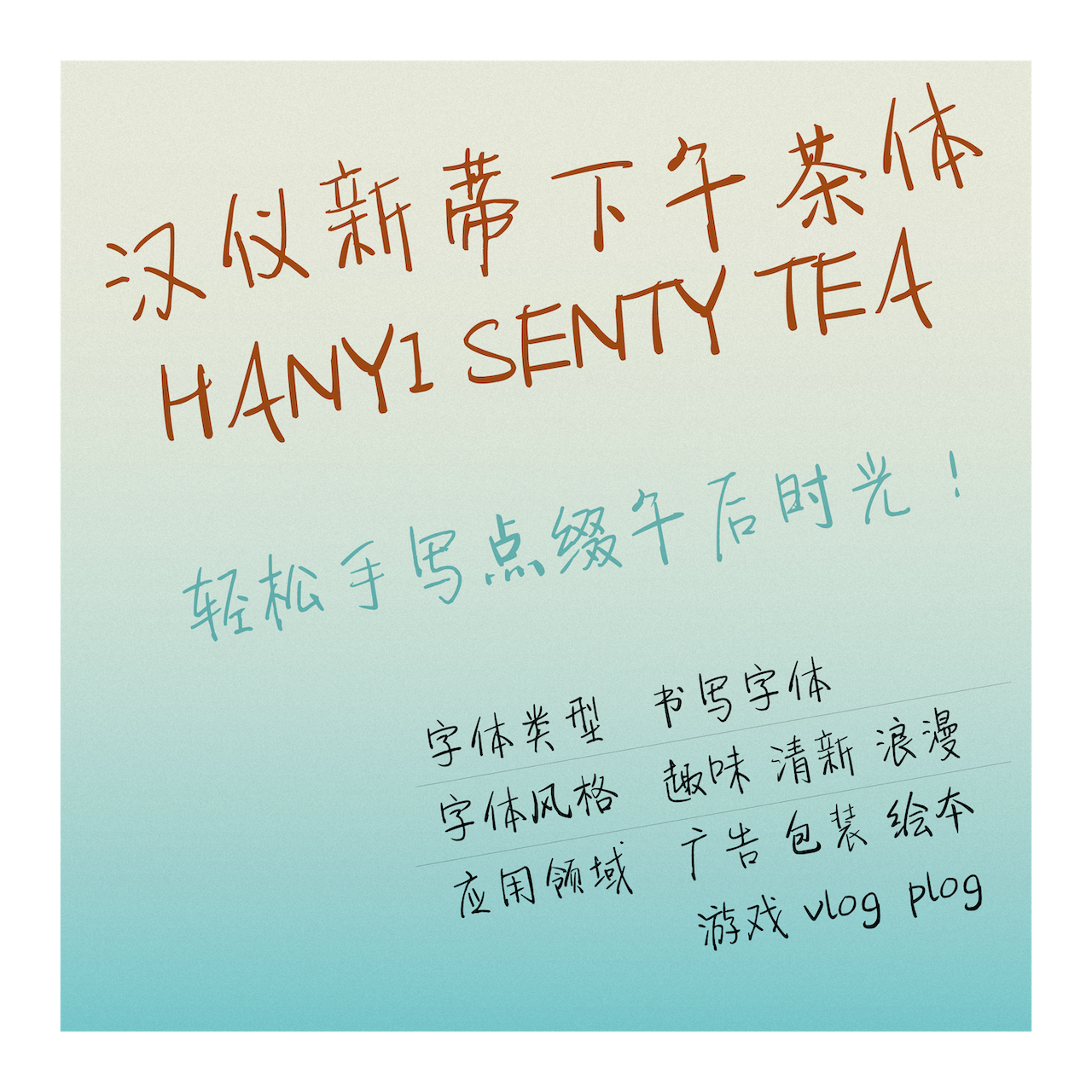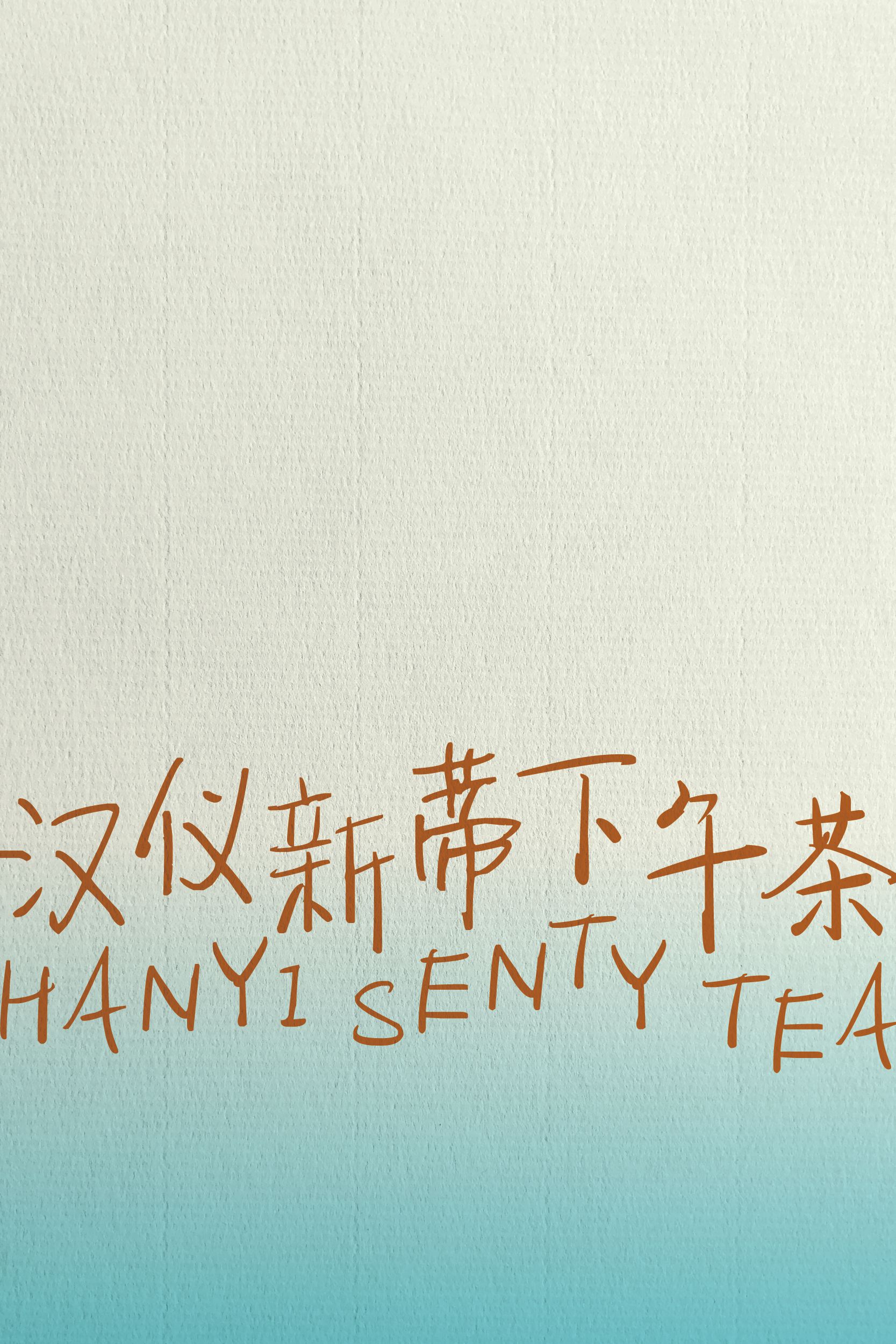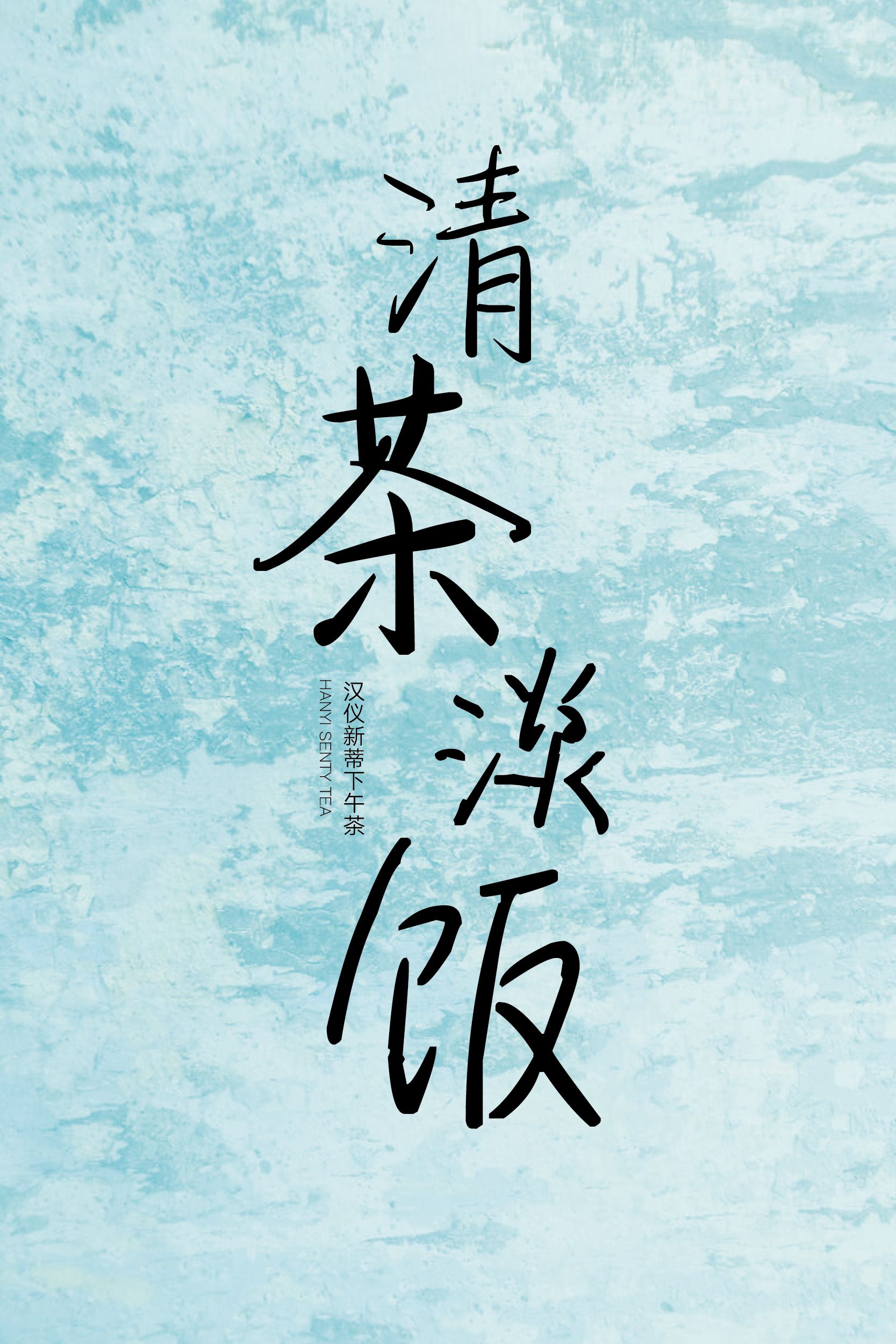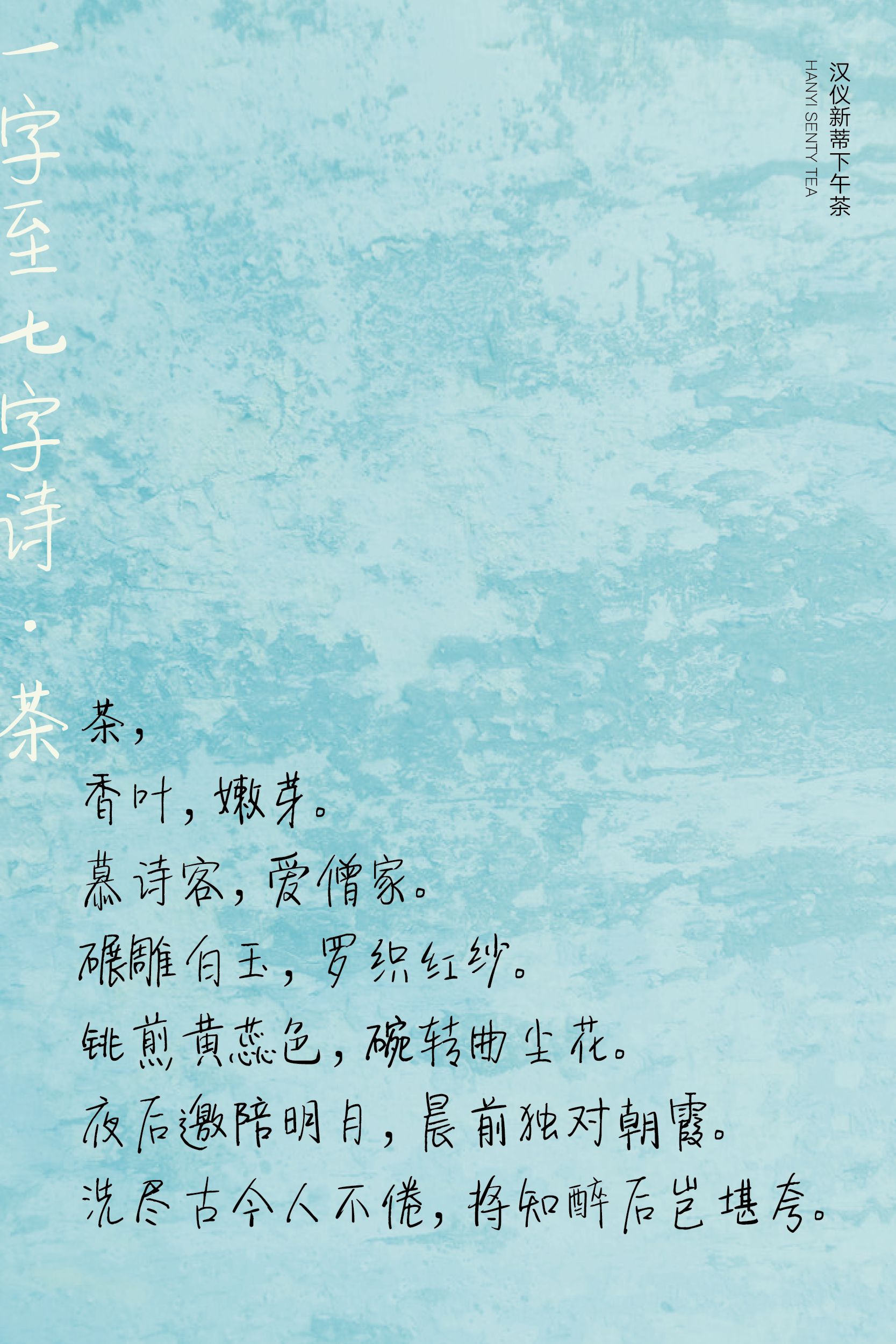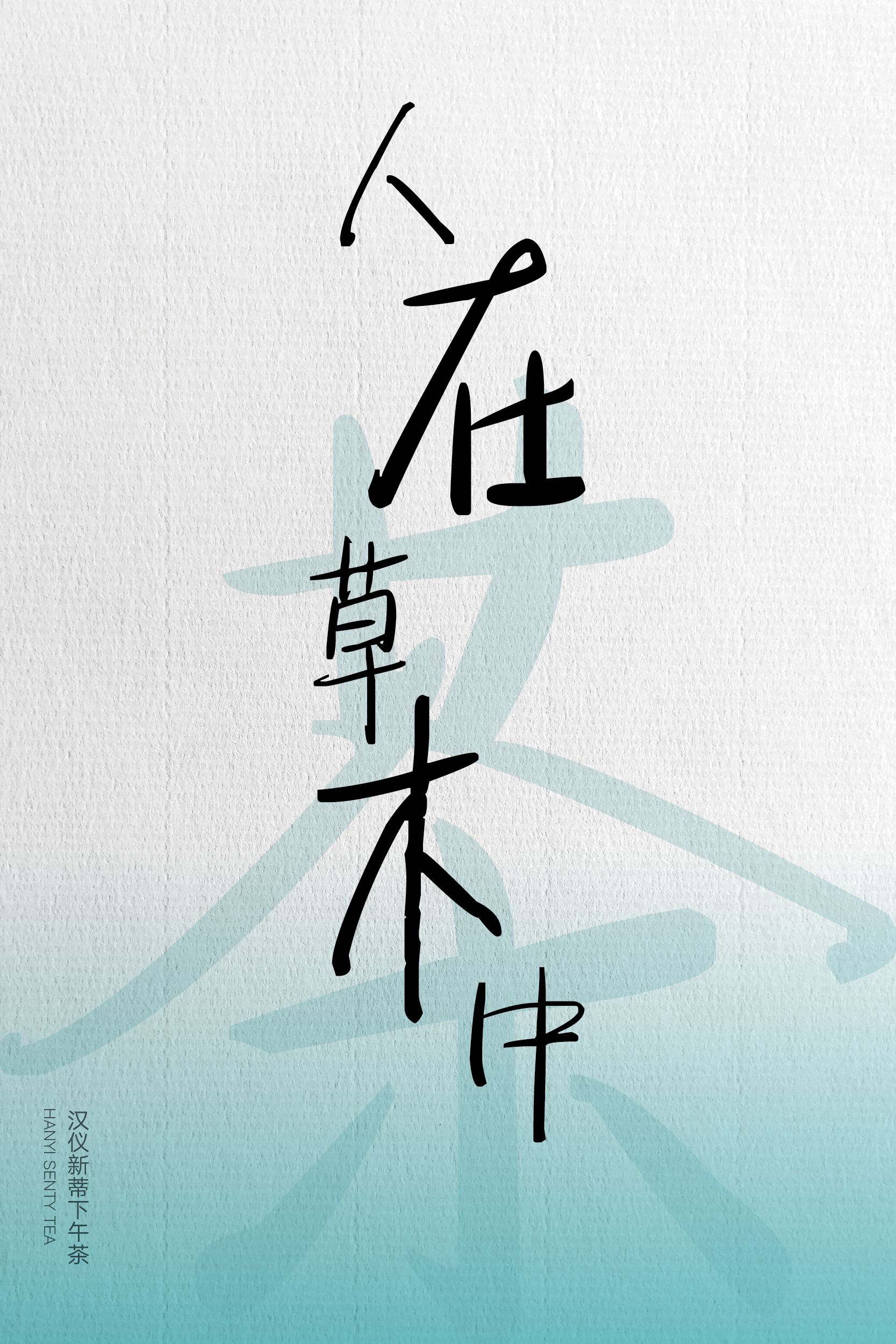
汉仪新蒂下午茶体
叮~下午茶时间到,汉仪字库和新蒂字体工作室邀请你来参加茶话会啦!汉仪新蒂下午茶体,以轻松手写点缀午后时光,让数字时代的设计排版拥有了书写的温度。无论是信函请柬、书籍绘本,还是广告包装、影音娱乐、vlog和plog等自媒体内容,汉仪新蒂下午茶体的出现就像是快节奏的生活中突然放慢的脚步,抑或是嘈杂的人群中一声轻柔的问候,为人们疲惫的身心带来一丝微风般的美好。
汉仪新蒂下午茶体|字体特征
自然随性,与美食适配满分。
手写字体传达了温馨友好的语气,令人放松。
希望这款字体如同生活中的小确幸,点亮你的心情。
汉仪新蒂下午茶体|字体样张